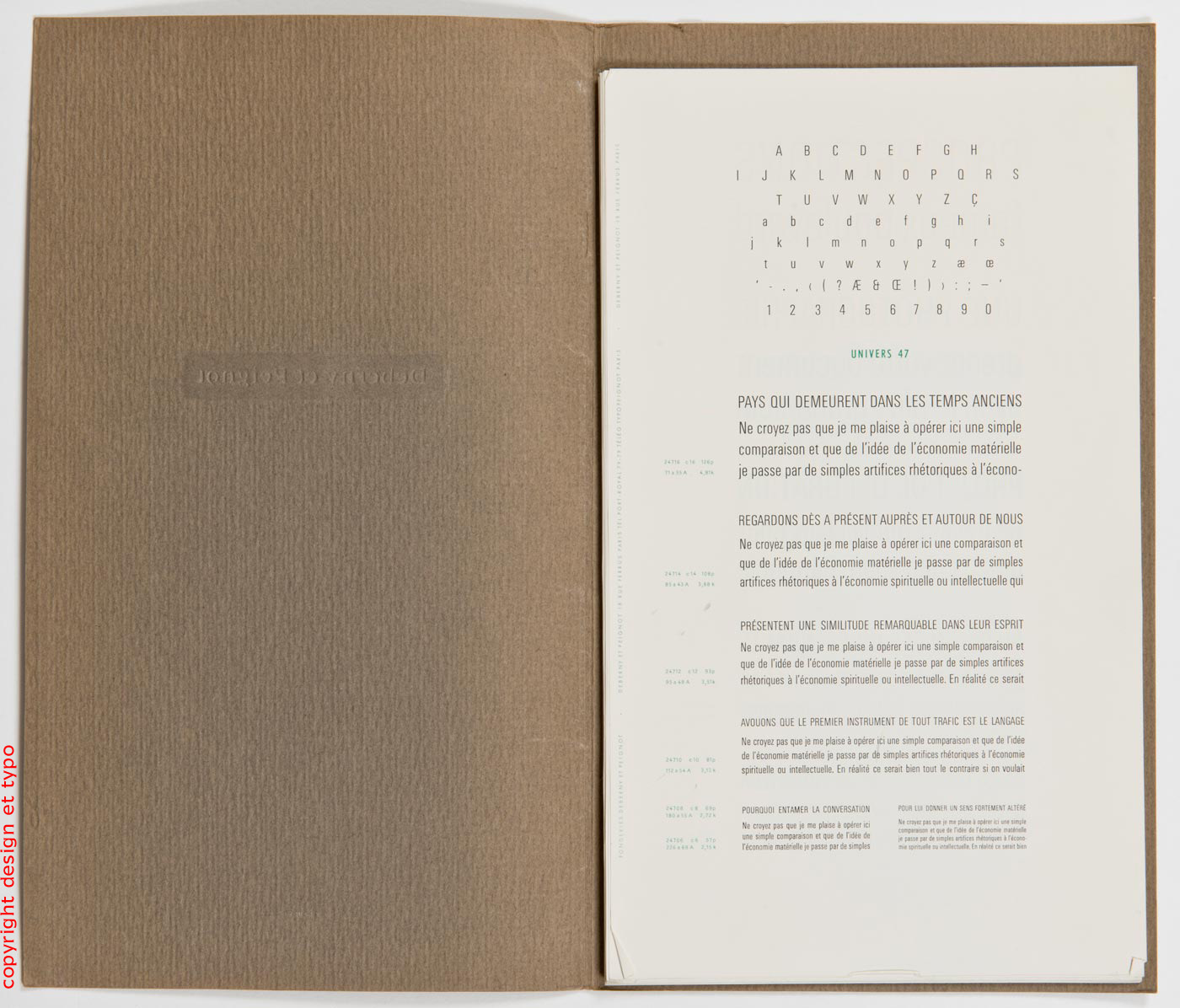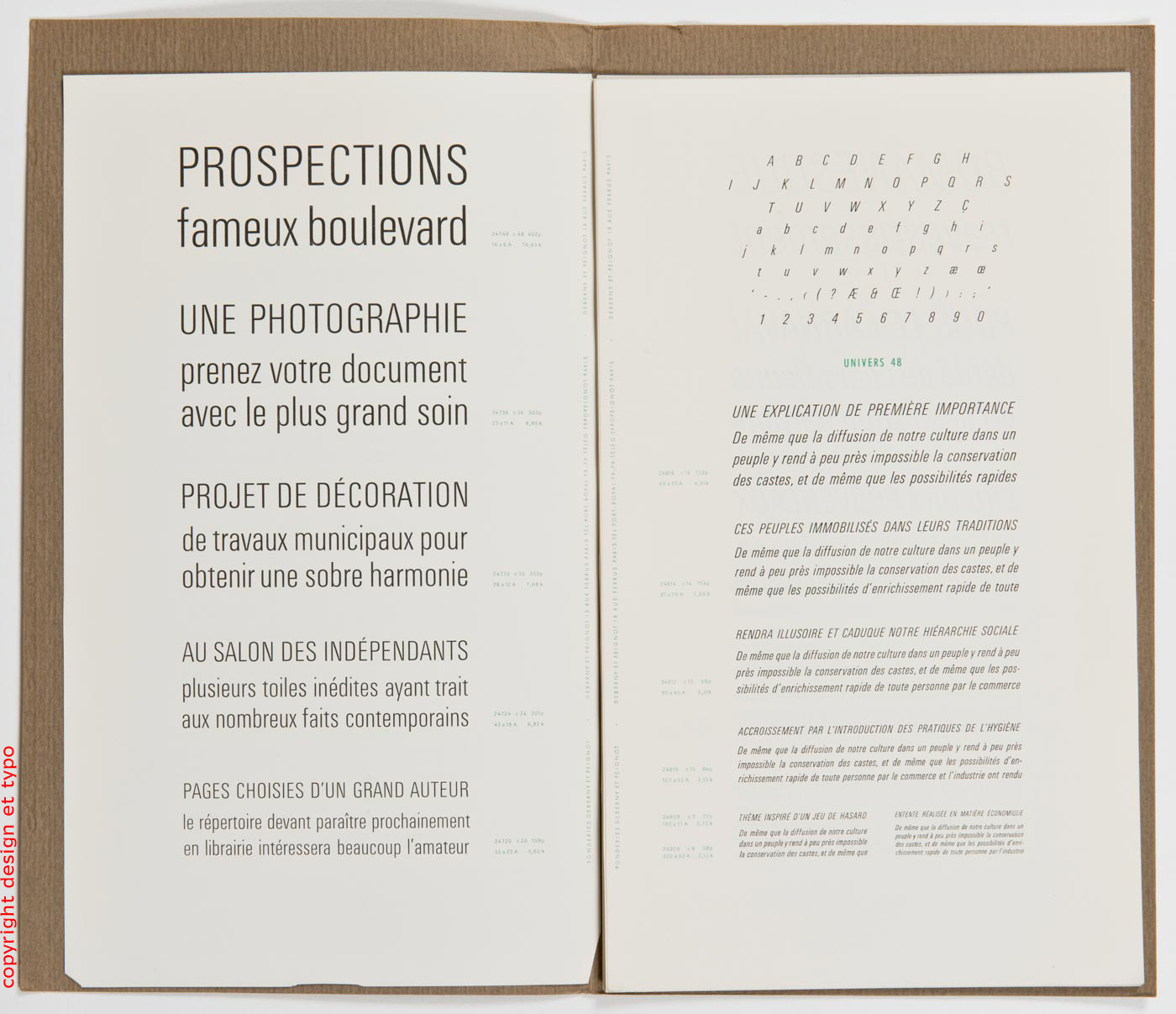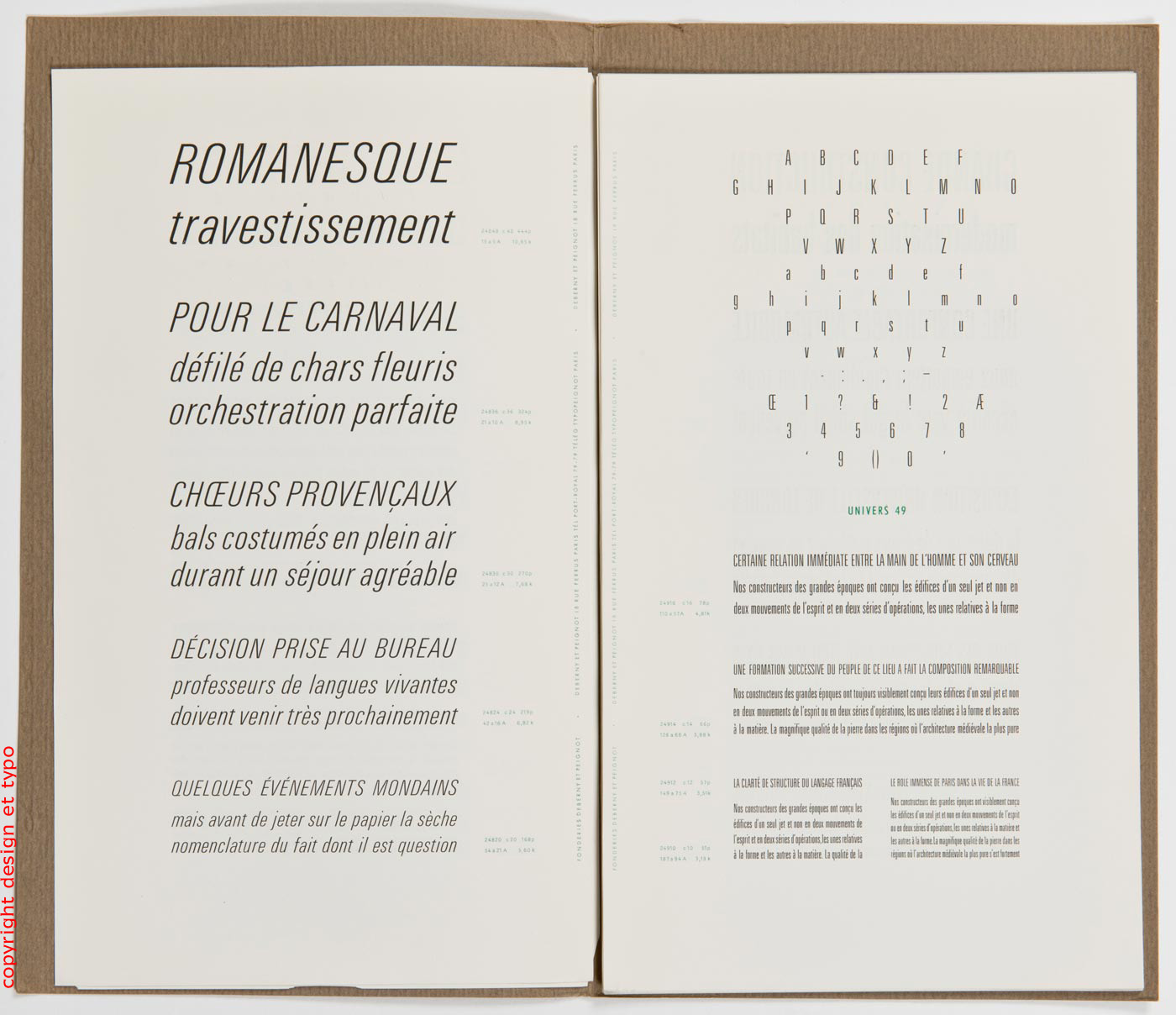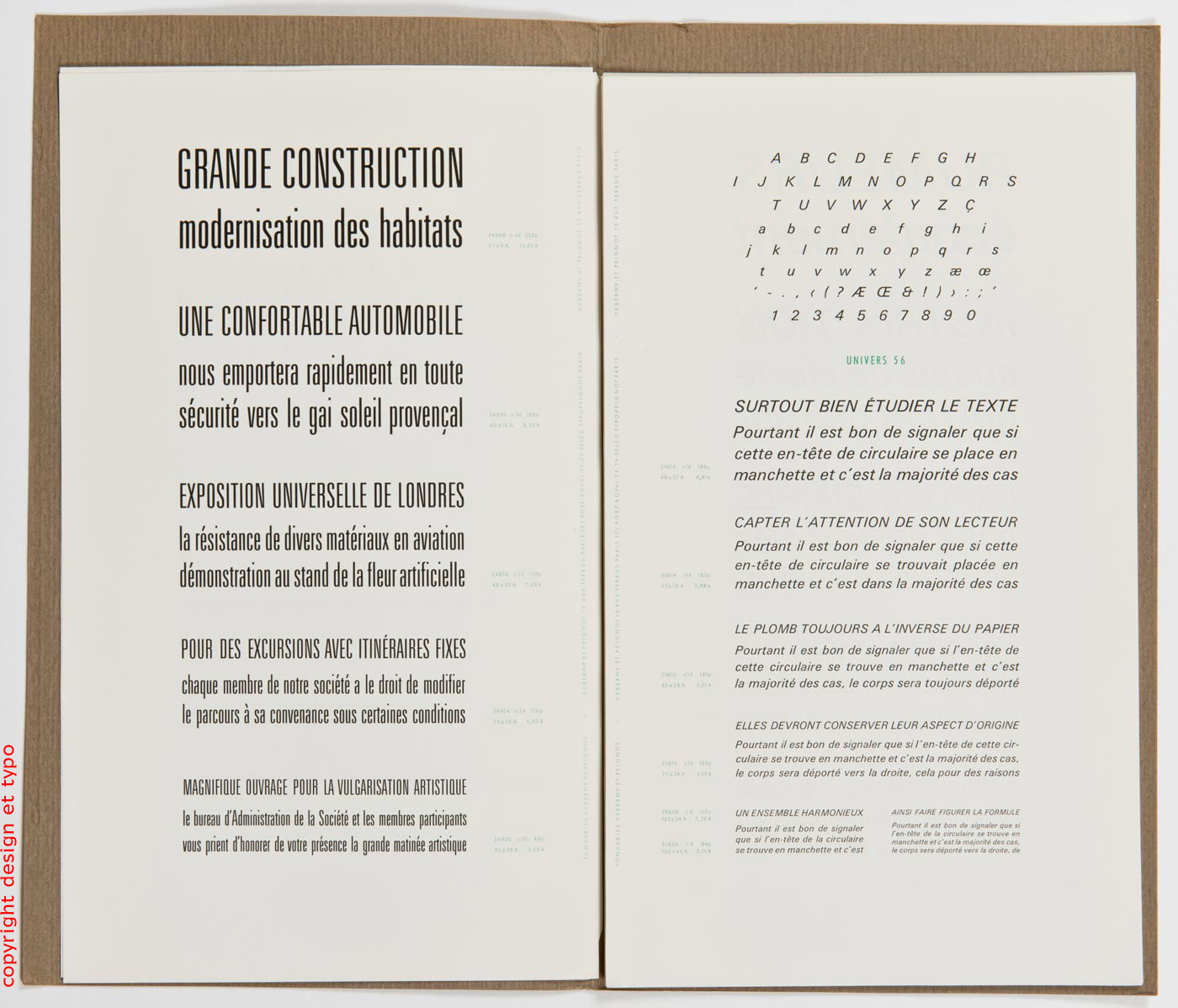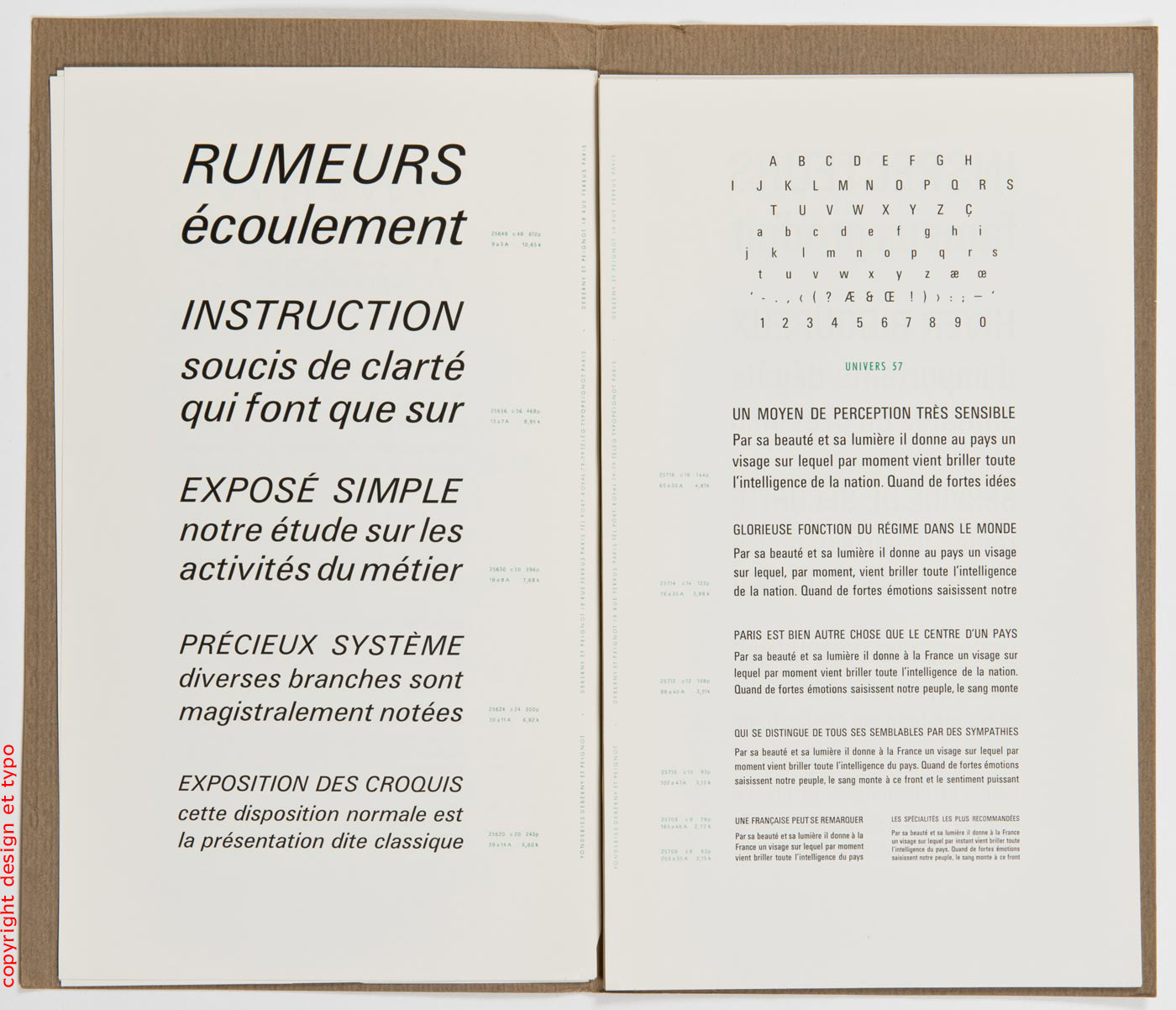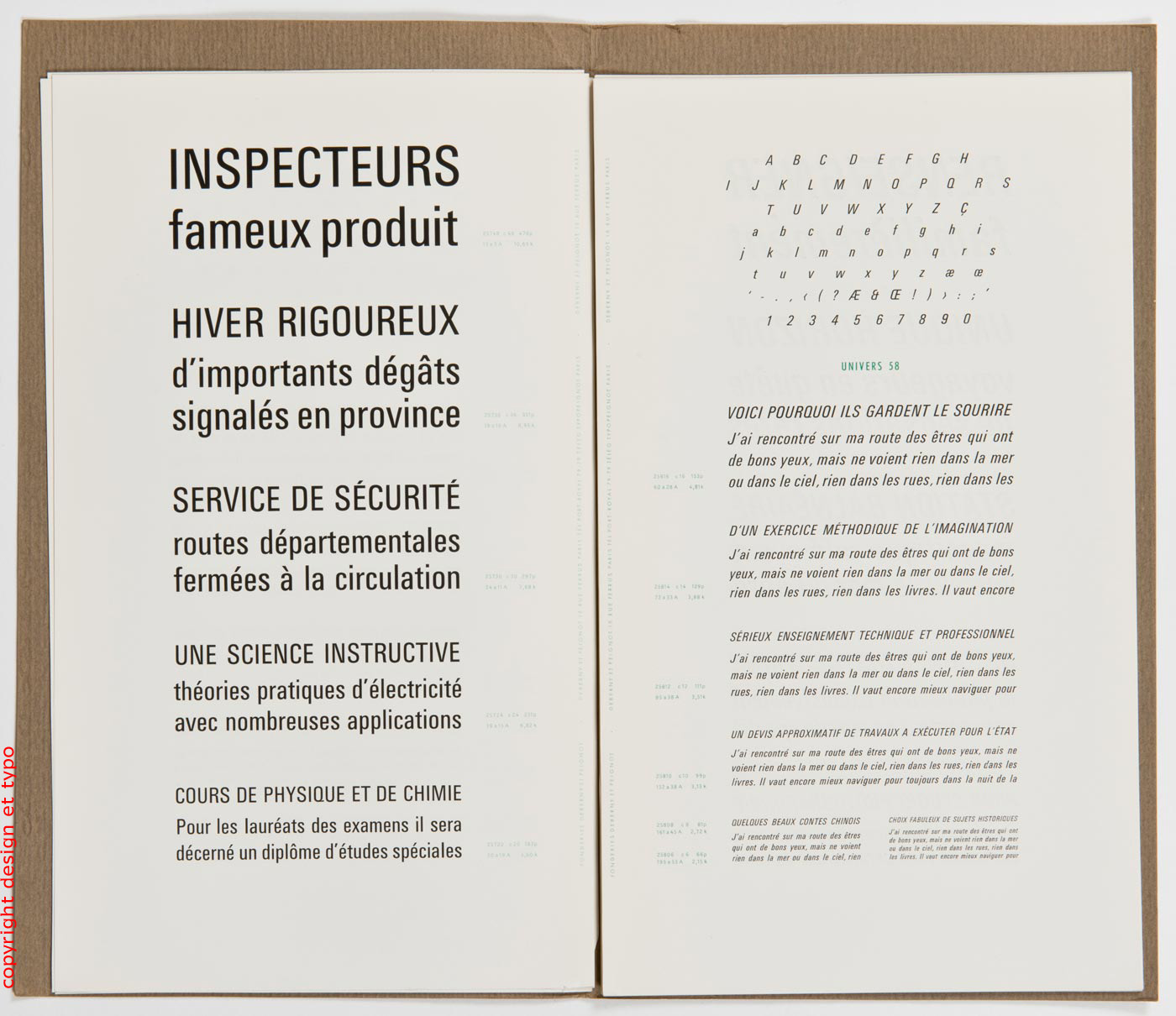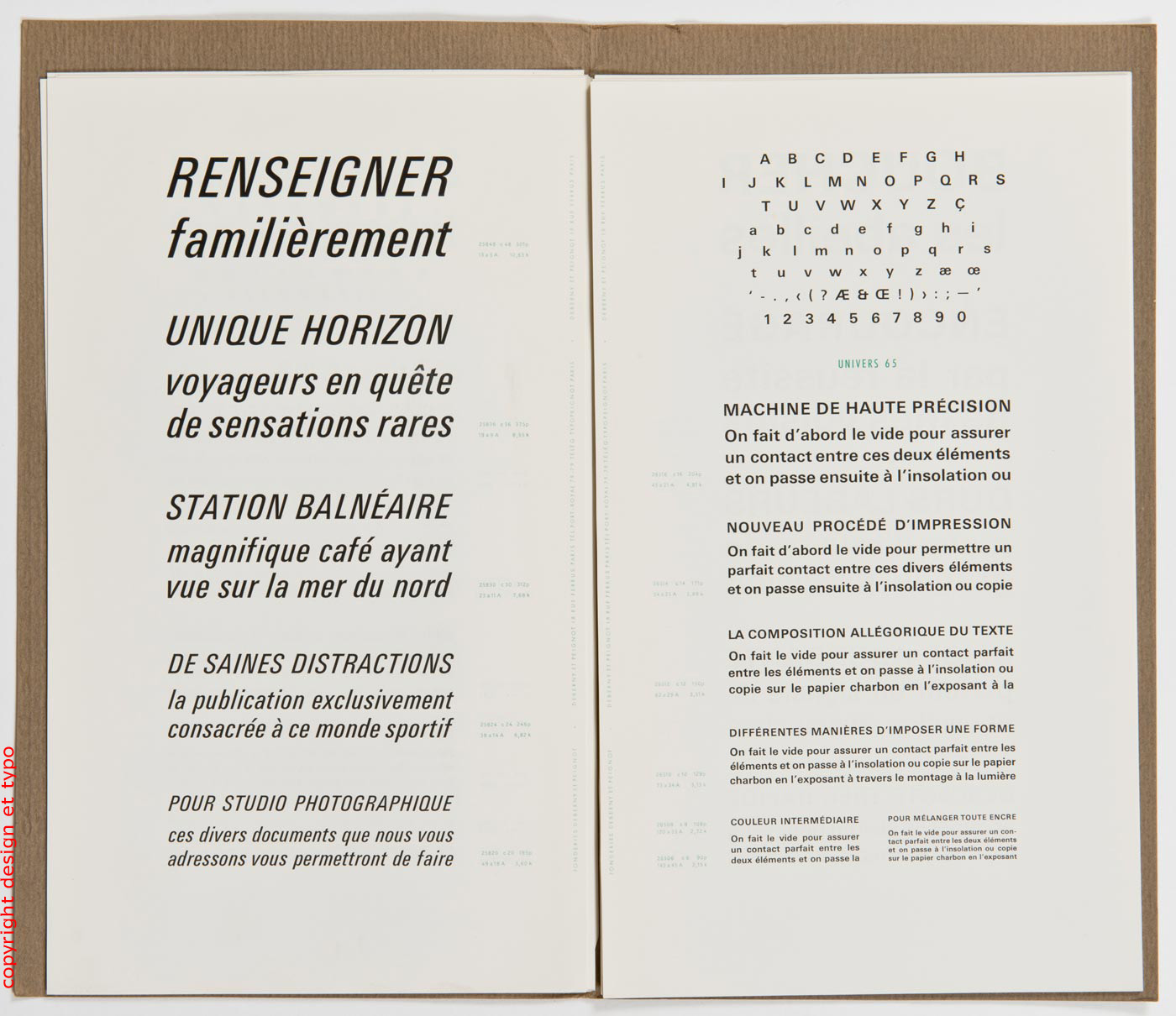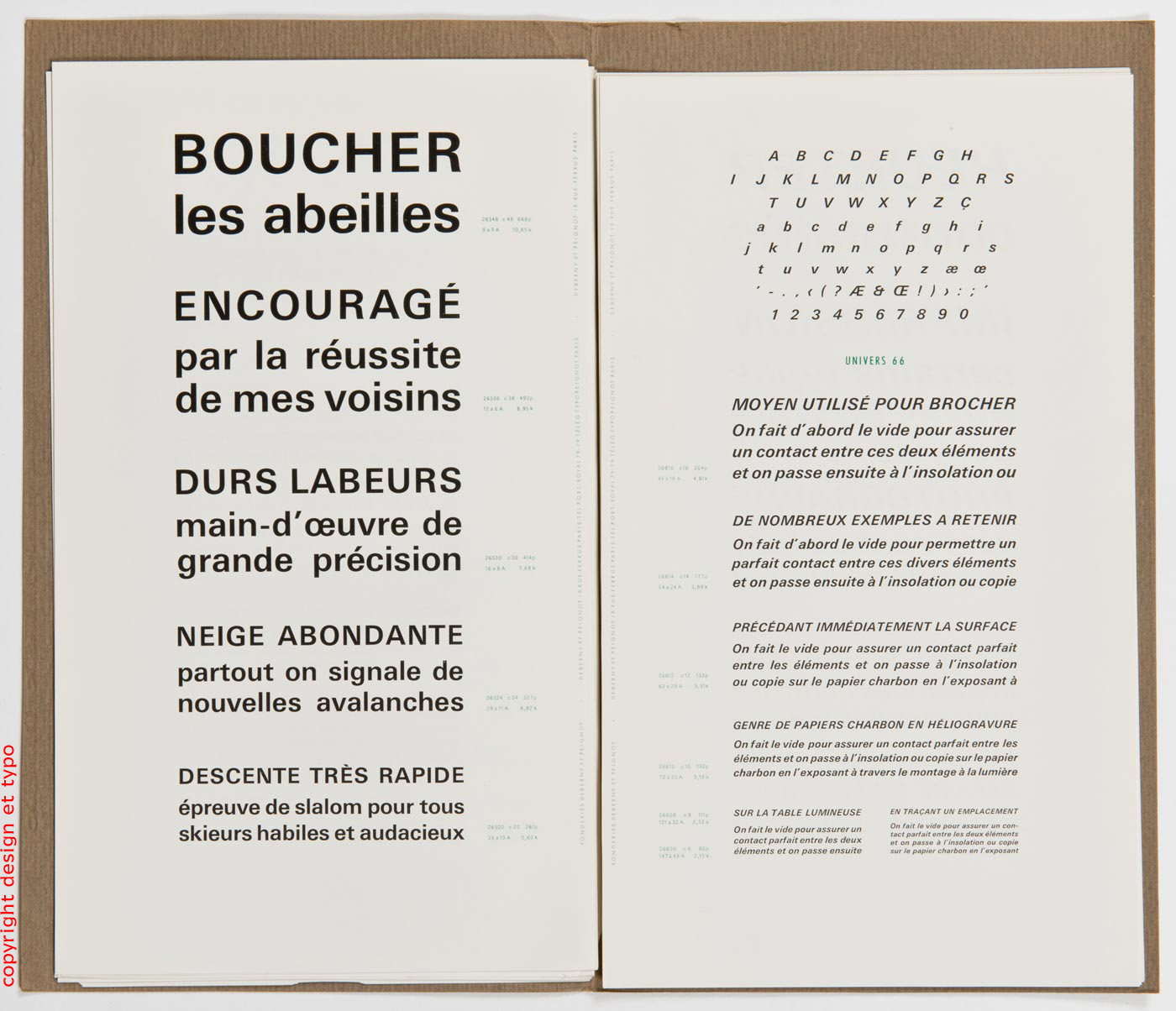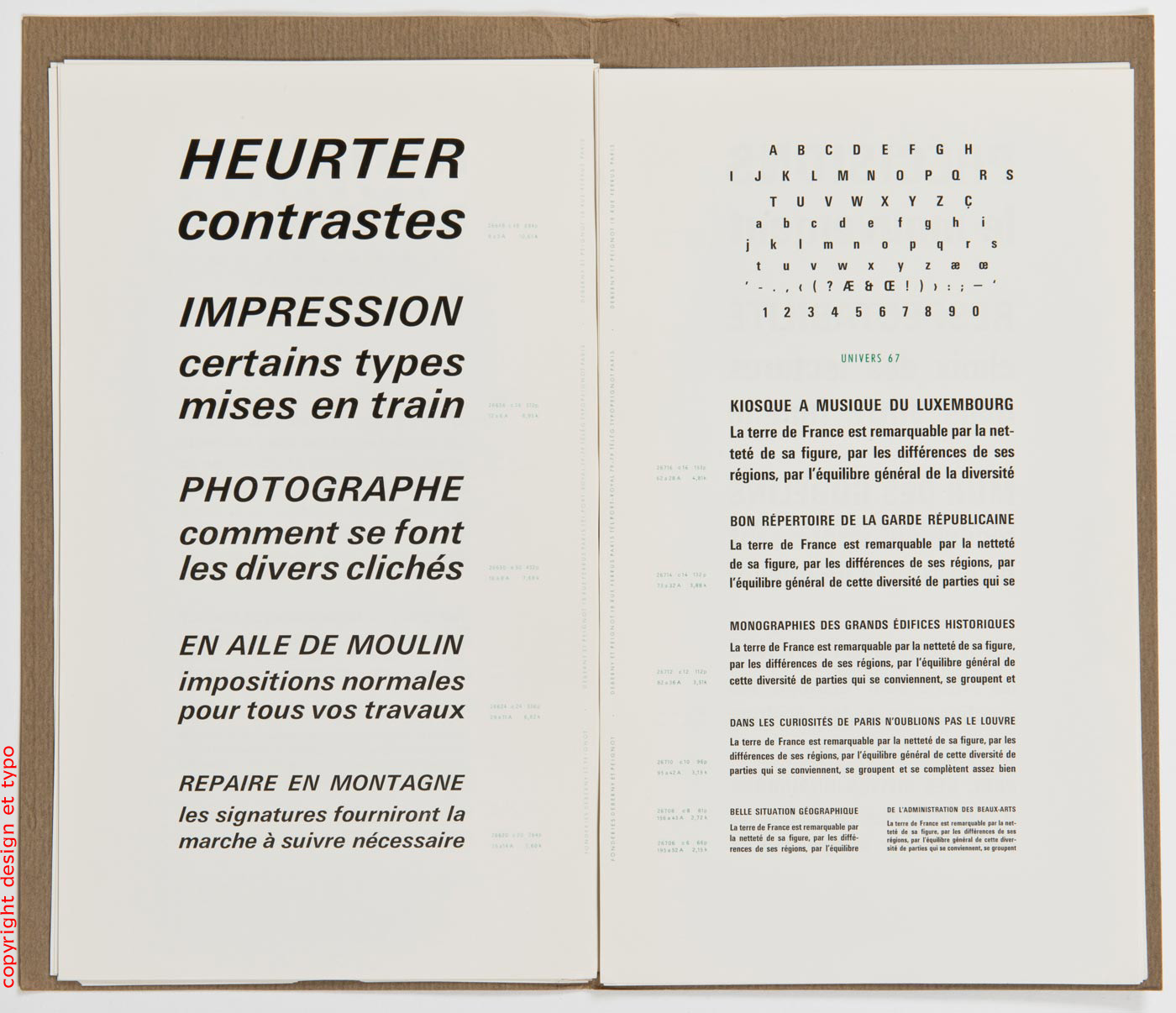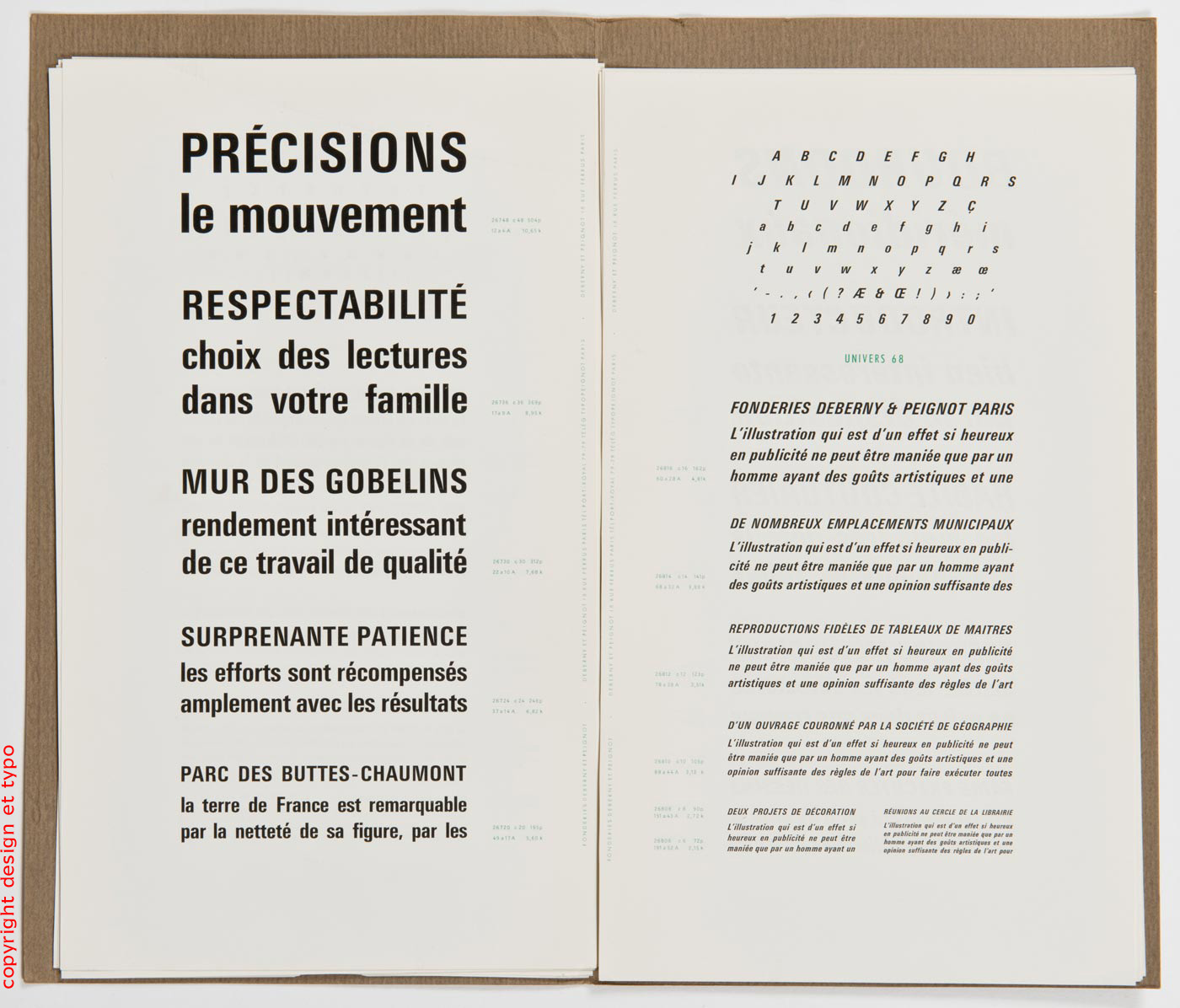
Univers d’Adrien Frutiger | Un specimen Typo de Deberny et Peignot | 1
Voilà typiquement le genre de spécimen de caractères qu’utilisaient les graphistes dans les années 50 et 60… Sans trop entrer dans l’histoire de la production pré-press, que j’ai par ailleurs déjà développé dans d’autres articles, il est nécessaire de rappeler aux jeunes futurs graphistes que les procédés de composition du plomb aux lettres de lumière (photocomposition) ont été toujours accompagné d’outils de calibrage des textes. En effet, nous parlons là d’une période de la production imprimée où l’ordinateur individuel n’existait pas encore. Il faudra attendre le milieu des années 80 pour voir apparaître des machines à traitement de texte. Secrétaires et dactylos allaient abandonner la machine IBM à boule pour taper des textes, les corriger et les enregistrer sur des floppy-disc de 5″1/4. Philips, IBM, Olivetti, et bien d’autres fabricants d’y étaient attelé de sorte qu’à la fin des années 80, les commandes des studios étaient souvent accompagnés par des textes déjà saisis.
Mais voilà, ça n’était pas encore le cas entre 1950 et 1980. Ce faisant tous les ateliers de composition étaient naturellement obligés de retaper les textes, voir de les composer au composteur en typographie-plomb-manuel. La Monotype ou la Linotype seuls permettaient de taper au clavier des textes qui étaient ensuite «fondus» avec un mélange de plomb et d’antimoine soit lettre par lettre (Montotype) ou lignes blocs par ligne blocs (Linotype). Les syndicats menaient par ailleurs des combats d’arrière garde contre l’avènement des modernités. Lorsqu’on songe que le journal Le Monde était encore composé en Linotype en 1982, alors que des ateliers comme typoGabor avaient déjà basculé leur production en composition digitale.
Question: à quoi pouvait bien servir un spécimen de caractères comme ceux de Deberny et Peignot (ci-dessous). Très simple. Il permettait aux graphistes ou directeurs artistiques de calibrer leur texte (tapé à la machine à écrire) avec un caractère d’imprimerie donné. Explications: chaque caractère a un encombrement horizontal qui lui est propre (la chasse du caractère). C’est moins flagrant entre un Garamond et un Janson maigres, mais bien plus évident lorsque vous comparer un Univers 49 à un Univers 55 (voir ci-dessous). Ce faisant, le graphiste calcule le nombre de signes que l’on peut entrer dans une ligne de corps 9 en Univers 49, de même il calcule le nombre de signes total de son texte «tapuscrit» (c’est-à-dire frappé à la machine à écrire) et il en déduit le nombre de lignes que son texte va occuper (pour une «justification» donnée et donc la hauteur de sa composition en multipliant le nombre de lignes par la valeur de l’interlignage. Ces opérations de calibrage entraient pour une bonne part dans le rôle du graphiste (et je vous montrerai des feuillets de textes ainsi préparées) et une fois rendu à l’Atelier de Composition, ils «atterrissaient» sur la table du «préparateur de copie» qui allait y rajouter quelques indications techniques pour le compositeur ou le claviste.
Bien que l’Univers d’Adrien Frutiger fut mis au point pour la photocomposition, il n’en fut pas moins fondu pour la composition manuelle (au composteur) et donc les graphistes avaient réellement besoin du genre de spécimen que voici.
Permettez-moi d’ajouter qu’au delà de sa fonction technique, un spécimen avait essentiellement pour vocation de présenter un caractère et le gris typographique qu’il allait «donner» une fois composé. Le graphiste qui met en page, textes et images, avait besoin de tels spécimens pour apprécier le résultat final escompté. Tout ceci était un travail très cérébral (nous sommes encore loin du WYSIWYG (What You See Is What You Get) mais je connais nombre de graphistes, jeunes et moins jeunes qui se souviennent très bien de l’usage de ces catalogues de caractères. En attendant prenez plaisir à zoomer sur chacune des pages. Vous cliquez et vous voyez alors la page de spécimen à taille quasi réel).